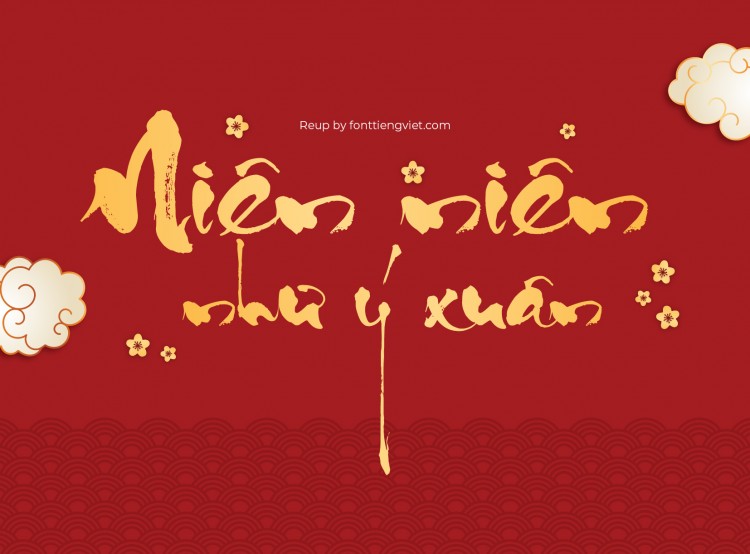
Font Thư Pháp Quang Ninh (2 font) ,font Tết
Font Thư Pháp Quang Ninh là một trong những kiểu chữ thư pháp nổi bật tại Việt Nam, mang trong mình vẻ đẹp tinh tế và sức hút đặc biệt. Được phát triển từ những nét bút truyền thống của nghệ thuật thư pháp, font này thể hiện sự kết hợp hoàn hảo giữa nghệ thuật cổ điển và hiện đại.
Đặc điểm nổi bật
1. Nét chữ mềm mại: Font Thư Pháp Quang Ninh có các nét chữ mềm mại, uyển chuyển, tạo cảm giác nhẹ nhàng và thanh thoát. Điều này không chỉ thể hiện sự khéo léo trong từng nét bút mà còn mang lại cảm xúc sâu sắc cho người đọc.
2. Sự đa dạng trong thiết kế: Kiểu chữ này thường được áp dụng trong nhiều lĩnh vực khác nhau như thiệp mời, banner, hay các sản phẩm văn hóa nghệ thuật. Tùy vào ngữ cảnh, người dùng có thể điều chỉnh kích thước và độ đậm nhạt của chữ để phù hợp với nội dung.
3. Ý nghĩa văn hóa: Font Thư Pháp Quang Ninh không chỉ đơn thuần là một kiểu chữ; nó còn mang trong mình giá trị văn hóa sâu sắc. Mỗi chữ cái đều được thiết kế với tâm huyết, thể hiện triết lý sống, tình yêu quê hương và lòng tự hào dân tộc.
4. Ứng dụng rộng rãi: Font này rất phổ biến trong các dịp lễ hội, sự kiện văn hóa và các hoạt động cộng đồng tại Quảng Ninh và các vùng lân cận. Nó gắn liền với các sản phẩm thủ công mỹ nghệ, tranh vẽ và những tác phẩm nghệ thuật khác.
Kết luận
Font Thư Pháp Quang Ninh không chỉ là một công cụ truyền tải thông điệp mà còn là một tác phẩm nghệ thuật độc đáo. Sự kết hợp giữa truyền thống và hiện đại khiến cho font này trở thành một biểu tượng văn hóa đặc sắc của vùng đất Quảng Ninh. Những ai yêu thích cái đẹp và nghệ thuật thư pháp chắc chắn sẽ tìm thấy niềm đam mê khi làm việc với kiểu chữ này.
Font chữ Quang Ninh Thư Pháp VNI ra mắt lần đầu năm 2007, được tác giả làm mới và cập nhật năm 2010. Từ đó đến nay, Phông chữ QuangNinh ThuPhap cứ thế truyền tay nhau qua nhiều thế hệ. Tên của bộ phông cũng là tên của tác giả Quang Ninh. Đáng tiếc, tác giả của bộ Font chữ Quang Ninh này không còn duy trì được trang web của mình và lâu không còn update. Vì thế, Gói Font VNI QuangNinh ThuPhap 1 năm 2007 và VNI QuangNinh ThuPhap 2 năm 2010 là mới nhất. Sau đó, một cô gái có tên Mộc Hạ đã cho ra mắt bộ MTD QuangNinh Thuphap 1 và MTD QuangNinh Thuphap 2 rất giống với bản gốc. Thương hiệu này vốn có truyền thống “làm mới” các bộ phông chữ cũ VNI chuyển sang bảng mã Unicode. Nên sự khác biệt có chăng là cách mã hóa, tức dùng bảng mã Unicode mới, còn thiết kế giữ nguyên.